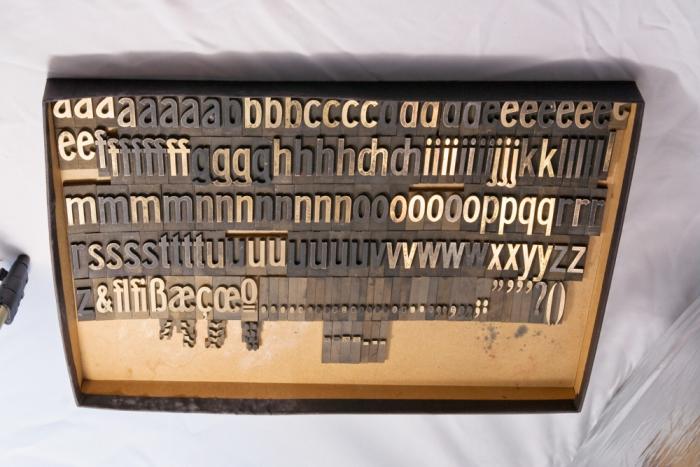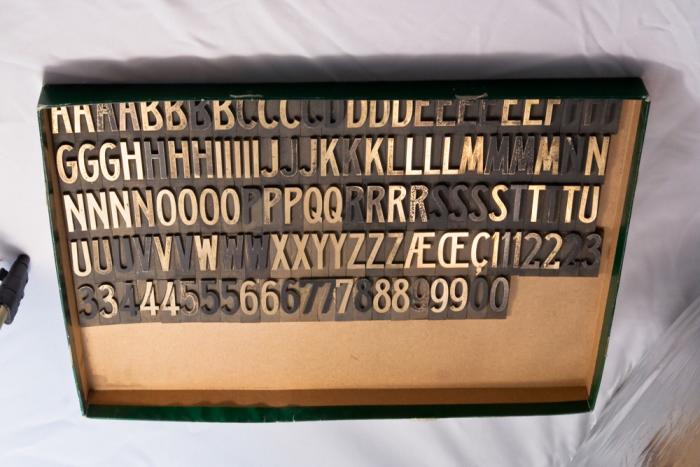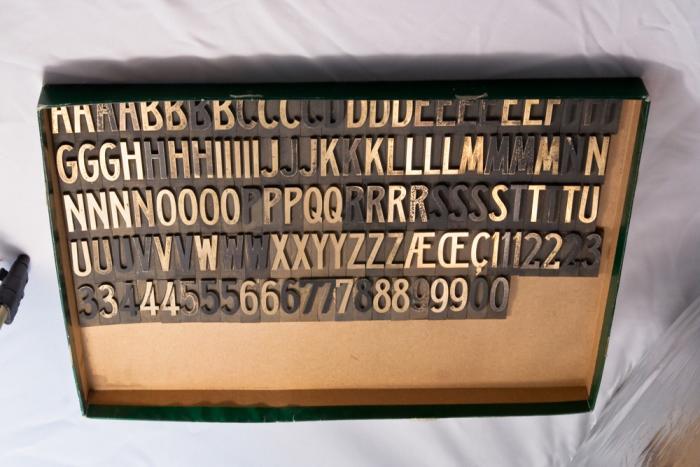
Alte Messing Prägeschrift (Grotesk) – wie mag sie heissen?
Moin, erkennt jemand diese alte Prägeschrift aus Messing? Ausgehend von anderen Schriften im gleichen Schrank könnte sie um und bei 100 Jahre alt sein.
Wenn das wirklich Messingbuchstaben zum prägen sind, beispielweise für Trauerschleifen, dann war es auch üblich das diese Schriften keinen Namen hatten. Meistens sind diese nicht von üblichen Schriftgießereien herausgegeben wurden sondern eher von Gravieranstalten. Die Schriften wurden meisten nur mit einer Nummer benannt und konnten so über den Katalog bestellt werden. Ich bin mal die Muster durchgegangen die ich habe, dort ist sie jedoch nicht dabei gewesen. Evtl. kannst du ja mal einen Druck anfertigen?